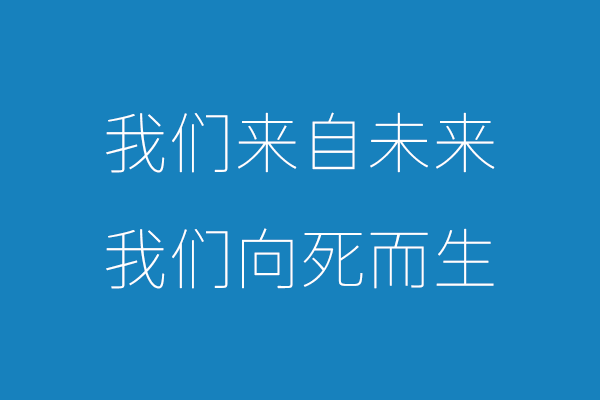
未来荧黑简体版
未来荧黑(Glow Sans SC)是一款基于思源黑体、Fira Sans和Raleway的开源字体项目,由Celestial Phineas设计。它支持简体中文、繁体中文和日文。
这款免费商用字体「未来荧黑」已经开放下载!它有9种字重和5种字体宽度,是基于思源黑体的7种字重扩展而来。整个字体家族共有44款字体,非常实用!
那么,未来荧黑与思源黑体有什么不同呢?
相比思源黑体,未来荧黑的造型更加现代化,版面效果更加清新轻快。它的中宫和字面更加收敛,重心在字重之间进行了重新配置;笔画细节的处理更加简洁干练,呈现出平直化的特点。
未来荧黑简体版效果预览
未来荧黑简体版字体效果预览